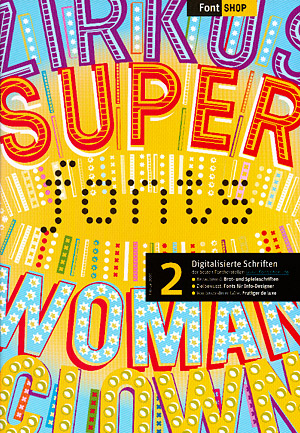
Font-Mailing von Fontshop
Wird in den nächsten Tagen verschickt: Die Februar-Ausgabe des Font-Mailings von Fontshop. Ich habe schon einen Blick darauf geworfen...
Unter anderem in dieser Ausgabe:
18 Zirkus- und Varietéschriften
Frutiger Next: vollendetes Leitbild. Die Überarbeitung beeindruckt durch mehr Strichstärken und eine echte Kursive.
Die Schriften des Comiczeichners und Illustrators Rian Hughes
und natürlich vieles mehr!